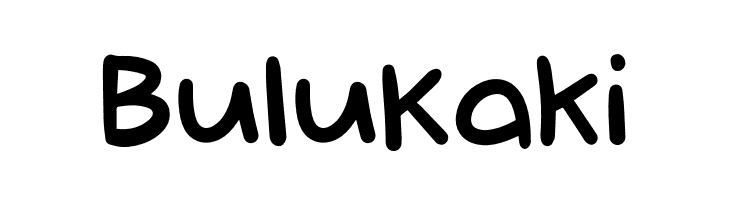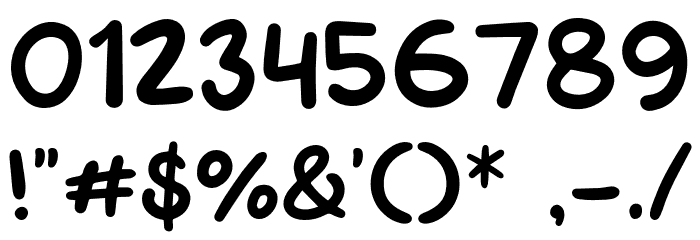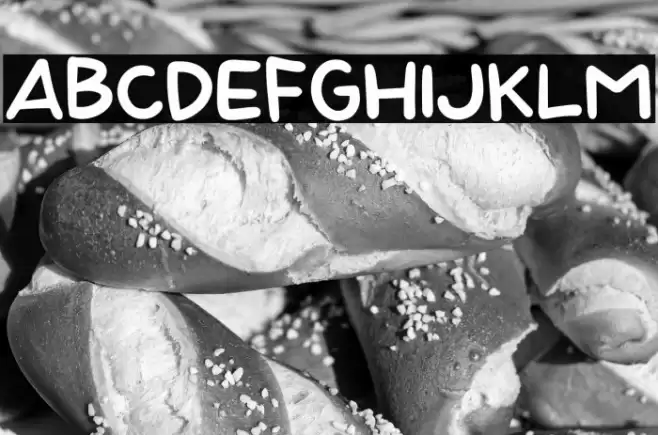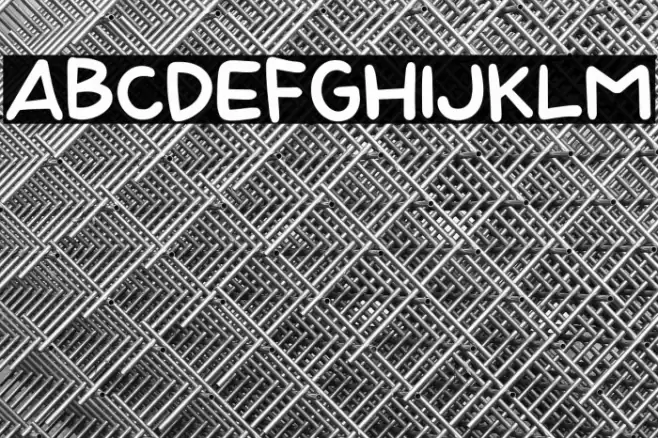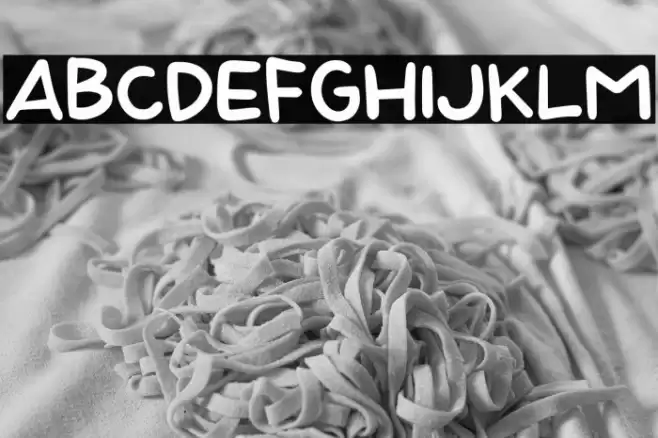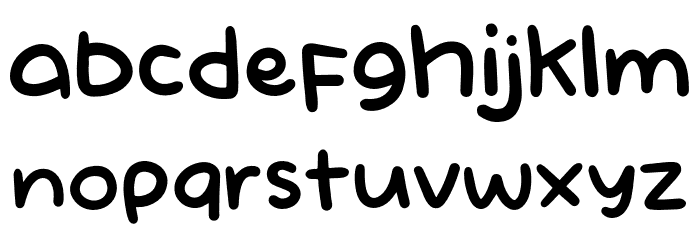
Bulu Kaki Font
✎ Cartoon
| Kategorien | Cartoon |
| Gesamtstil | Playful |
| Anwendungsfall | Logos, Headlines, Informal Text |
| Vorgeschlagene Projekte | Ideal for children's books, playful branding, greeting cards, and informal invitations. |